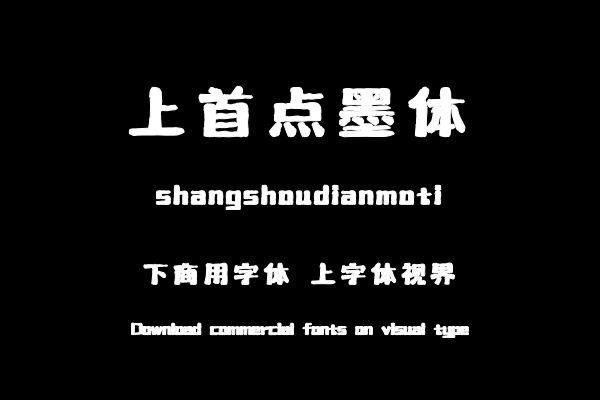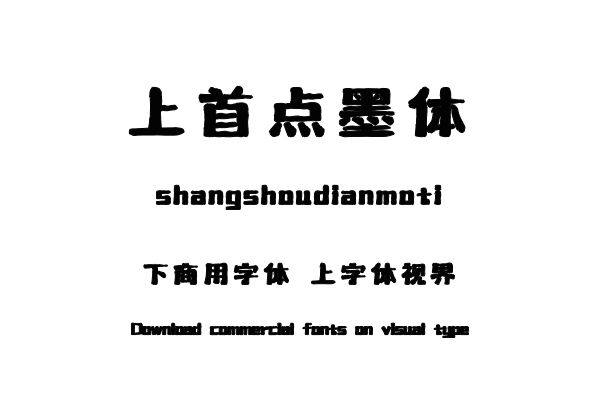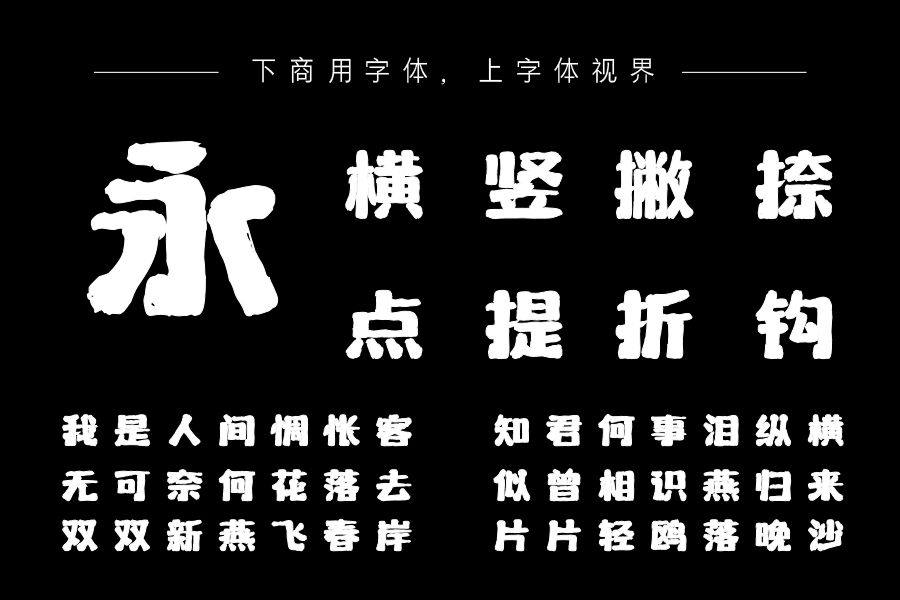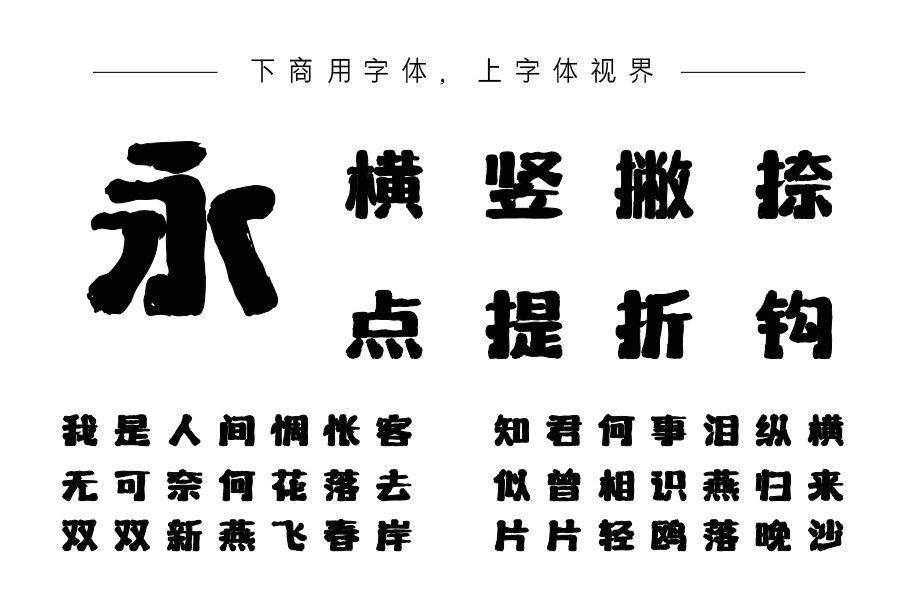
上首点墨体的笔画较为随意、洒脱,整套字体比较创意,类似毛笔的触感透露出一种孩童活泼童真的感觉,字体个性鲜明,艺术感十足。购买须知:“下载服务费”与“字体VIP”所获得字体 仅用于个人非商用, 商用请联系付费授权。本字体为电脑用字,手机没有root权限不支持直接手机换字(手机如何root,请自行百度搜索教程)。购买前请先 了解清楚后再付款 ,字体为虚拟产品无法回收 一旦购买不支持退款。